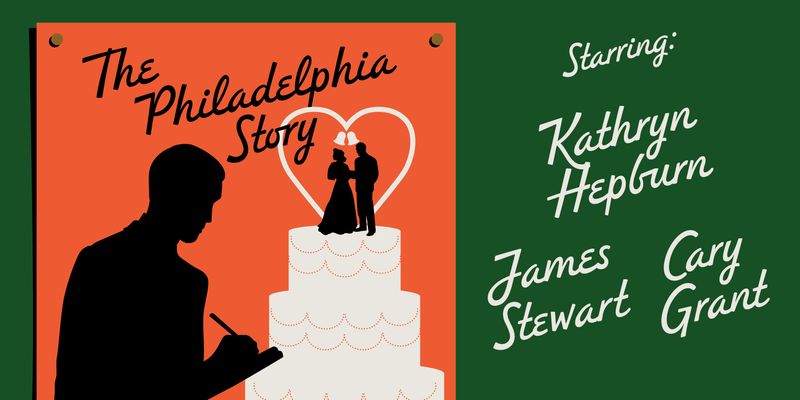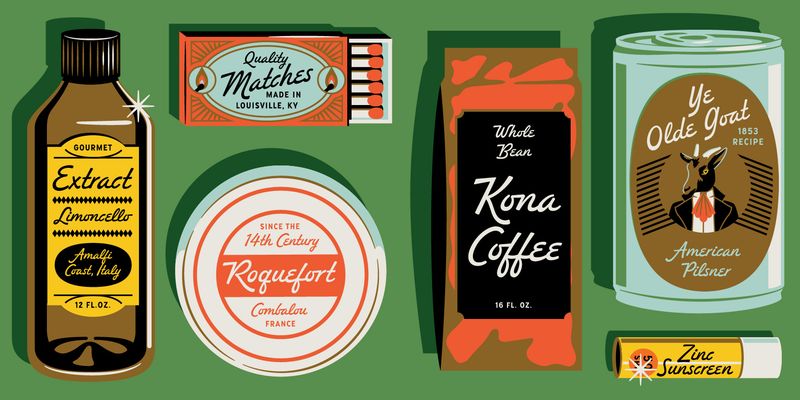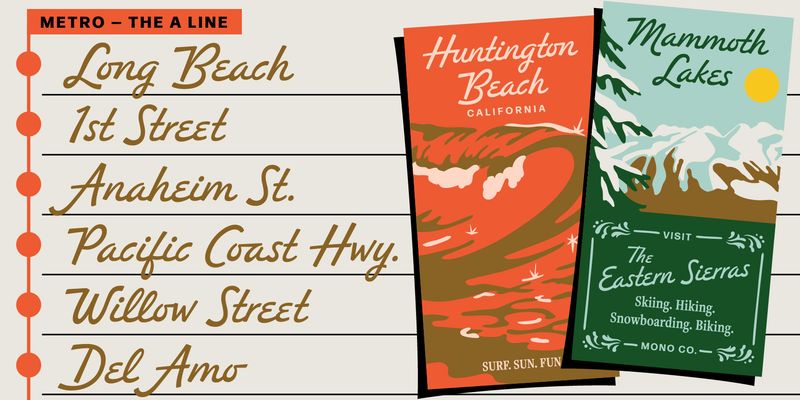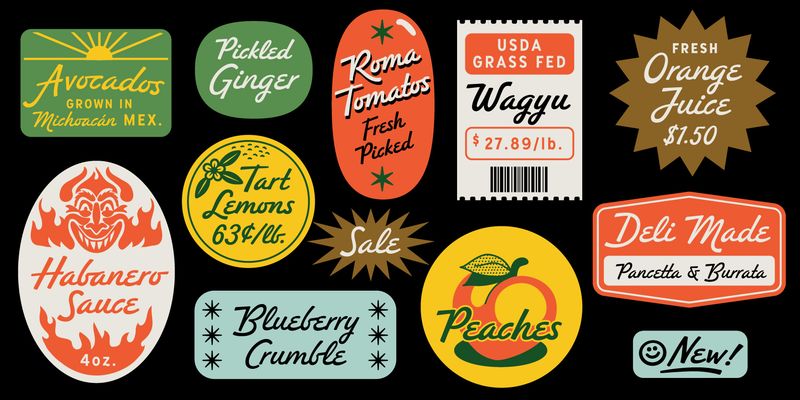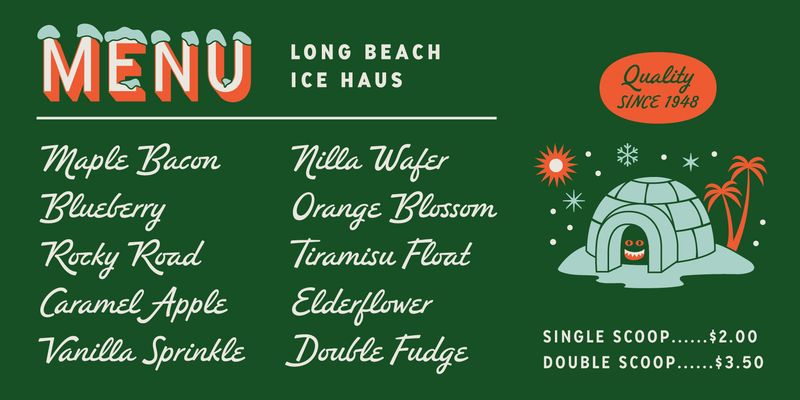
El estilo de letra Redondo Ave es una fuente orgánica, informal pero suntuosamente especial que puedes vestir de manera formal o informal. Redondo Ave viene en 2 grosores y cuenta con 560 pictogramas. Esta fuente de inspiración retro aporta personalidad al instante a cualquier diseño o formato. Al igual que Jennifer Coolidge, desprende una extravagancia que al mismo tiempo tiene los pies en la tierra.